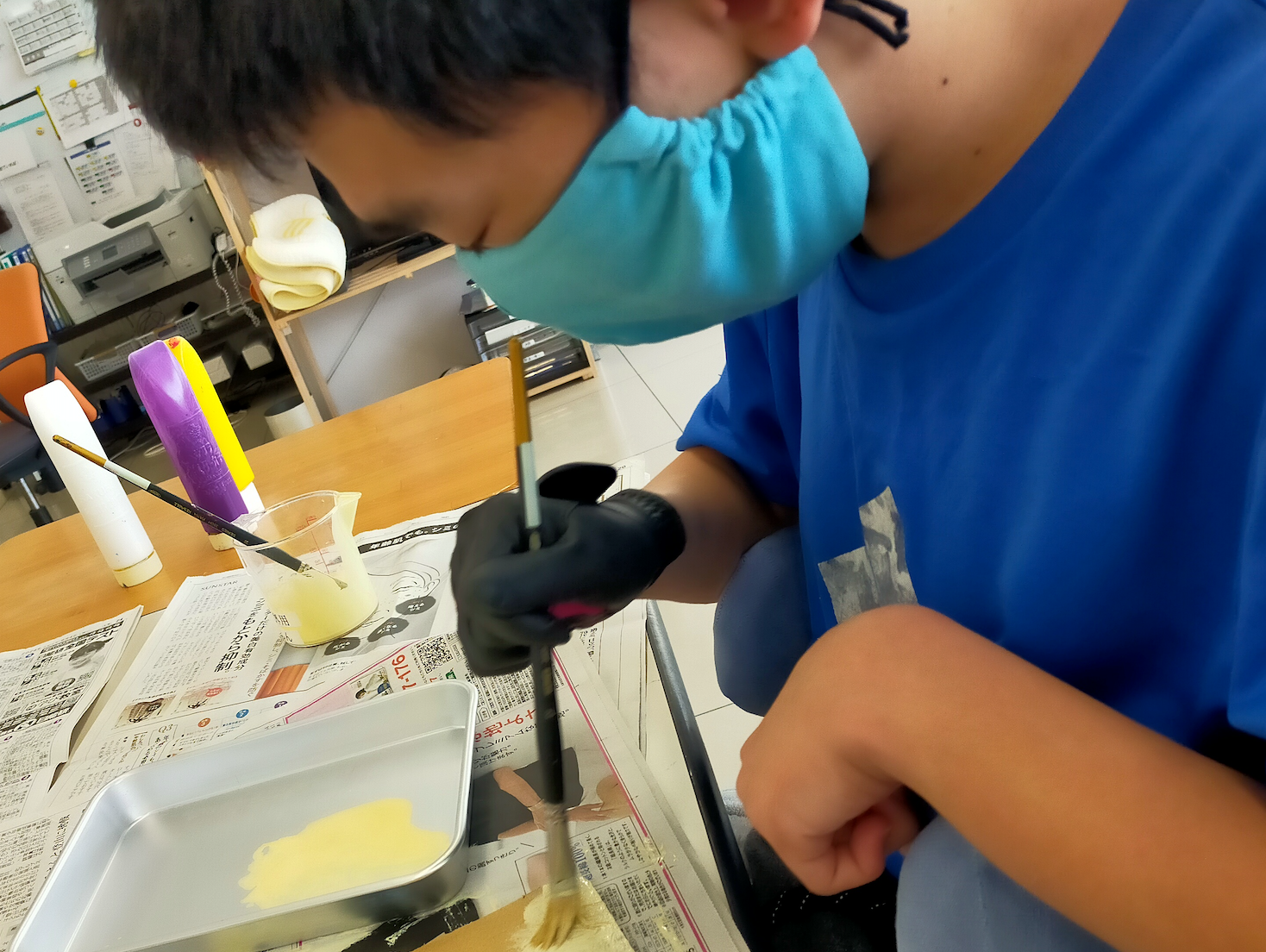
つながるかたち、つながる文字
みえフォント(三重県松阪市)
みえフォントは、重度障がいのある方たちとデザイナーが連携して生まれたフォントです。
動きに制約があっても、動きや道具を工夫することで、丸、三角、線など描けるかたちがあります。
その一つひとつを大切につなぎ、
文字としてかたちにしました。
自然が多く、気候が穏やかで、
人を迎える文化が根づく三重。
その土地の空気のように、このフォントも、
人に寄り添う存在でありたいと考え、
ひらがなで表現しています。
みえフォントは、多様な動きから生まれた、
三重らしい温もりのある文字です。